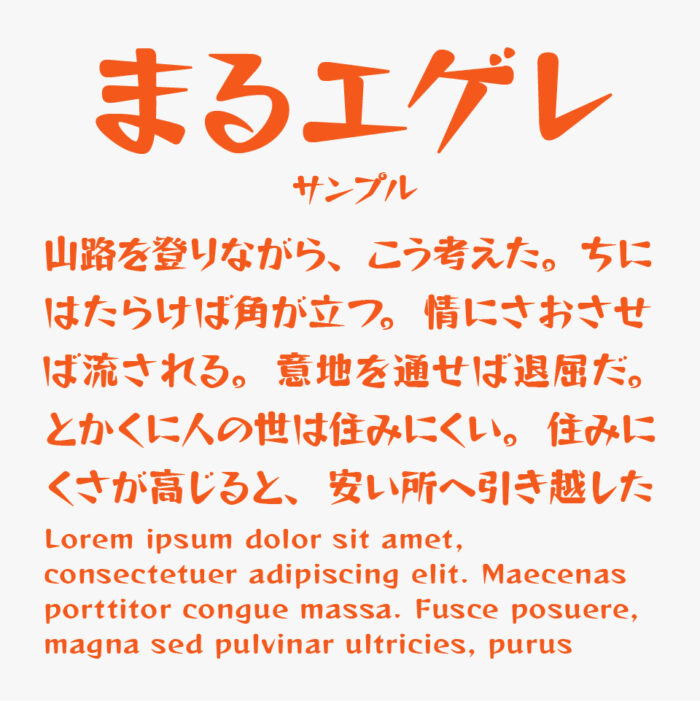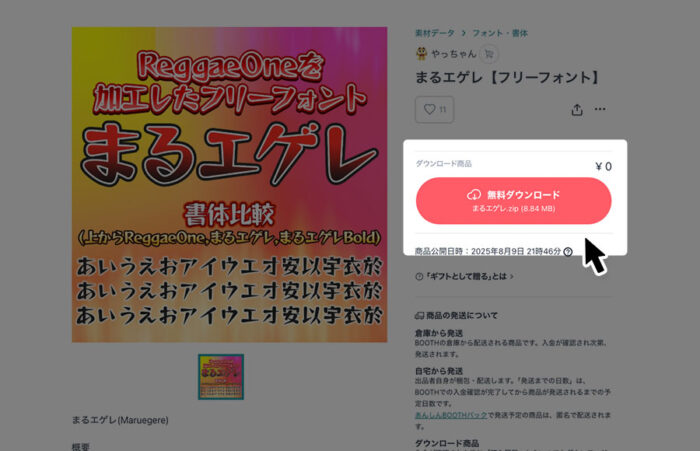
まるエゲレフォントは、レゲエOne(Reggae One)フォントをベースに、角を丸く処理されたデザインフォントです。
丸みのある形状になったことで、レゲエOneの鋭い印象から、ふっくらとした可愛らしい印象のデザインです。
文字の書き始めが丸みがあり太くなっていて、書き終わりにかけて細くなっていくフォルムは筆文字のような雰囲気も感じるフォントとなっています。